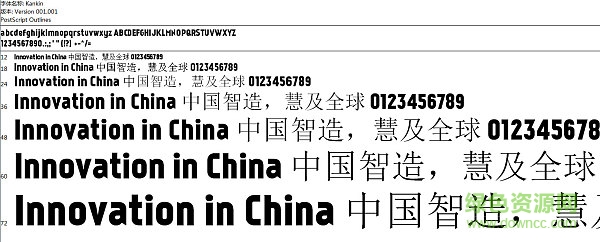
kankin英文字體
Kankin字體是一款超好用的英文字體,KanKin是一款具當(dāng)代感的無襯線字體,由俄羅斯設(shè)計(jì)師 Alexey Frolov 制作而成,帶著“老風(fēng)格”的無襯線,適合于海報(bào)、Logo、印刷以及網(wǎng)站。有喜歡這款字體的朋友就趕快來綠色資源網(wǎng)下載使用吧!